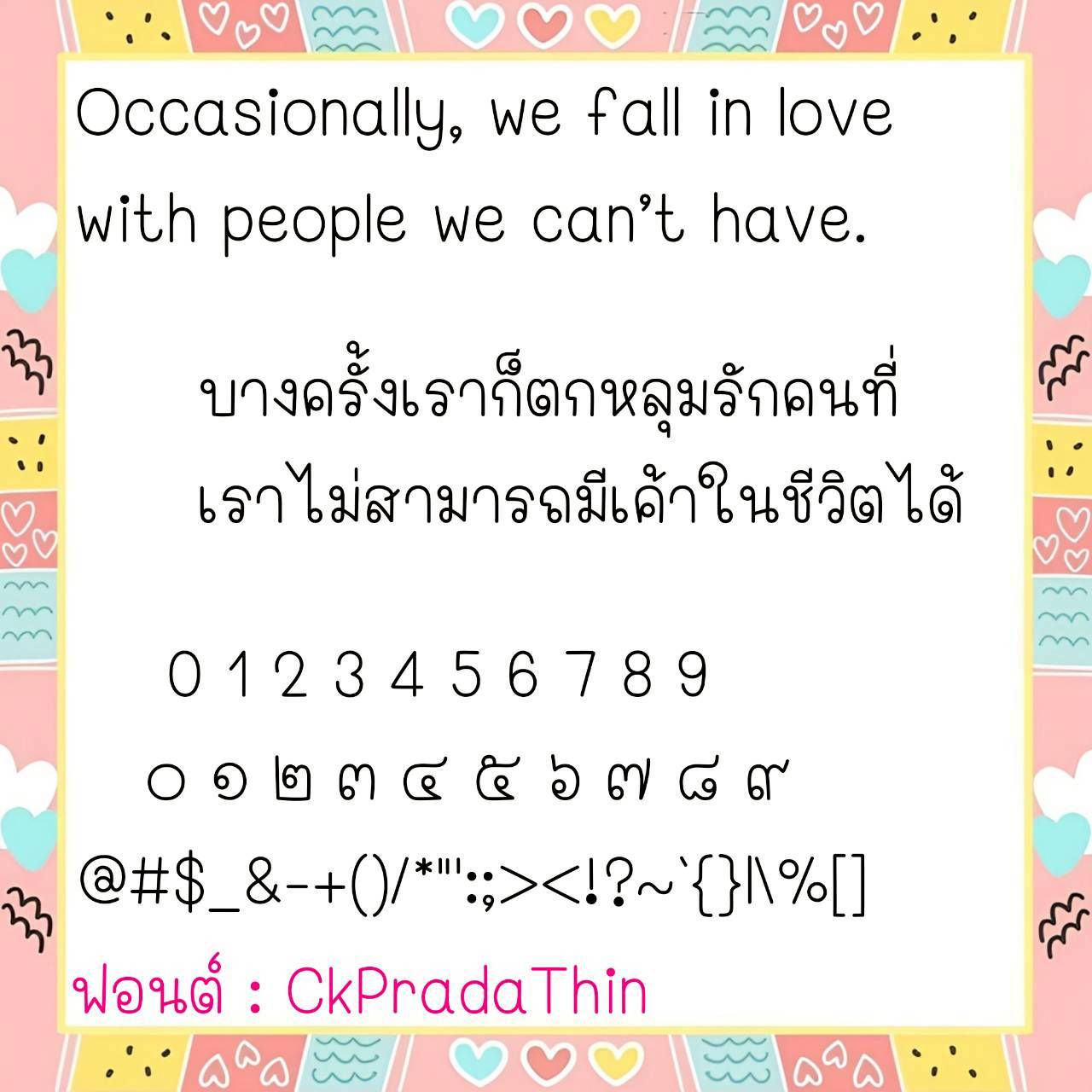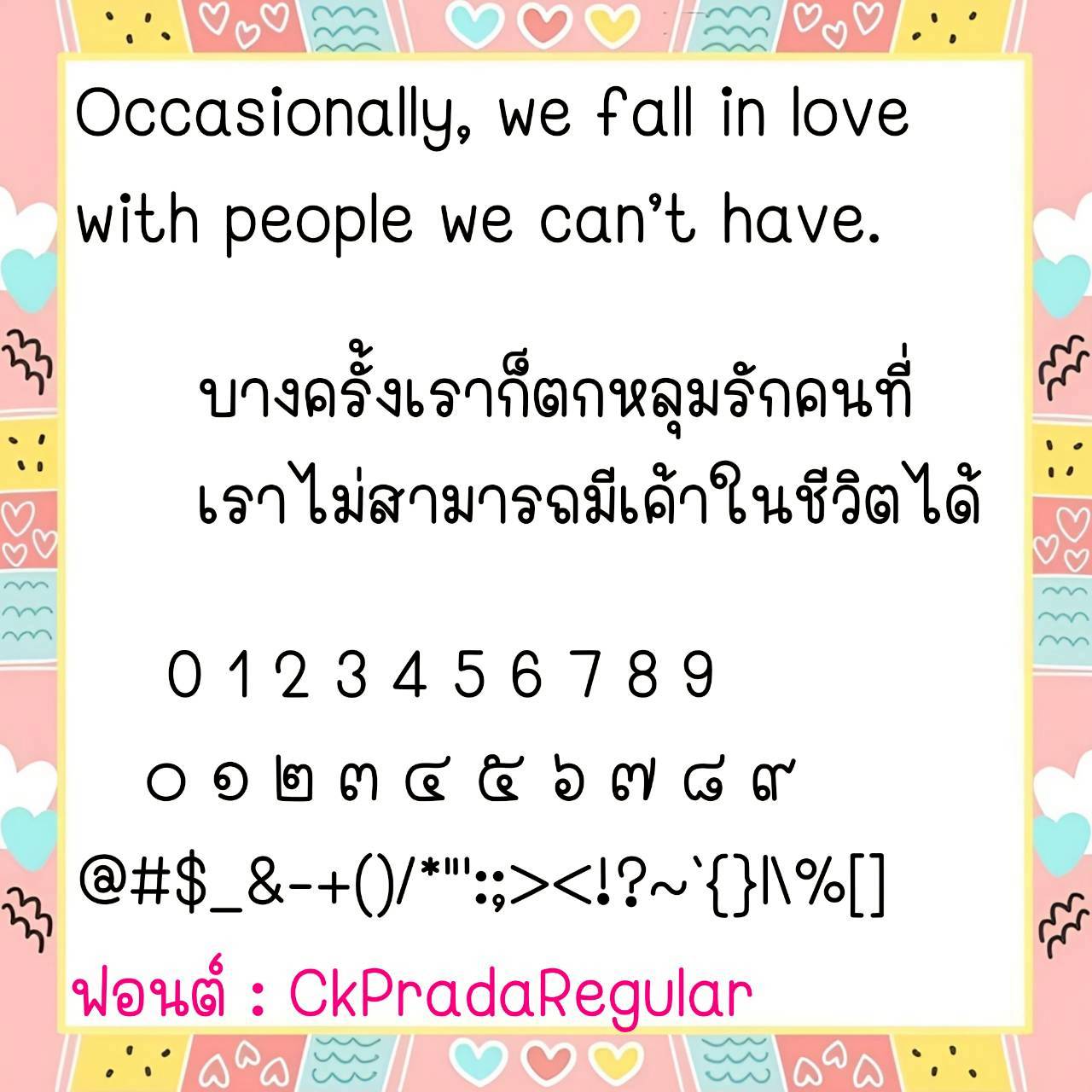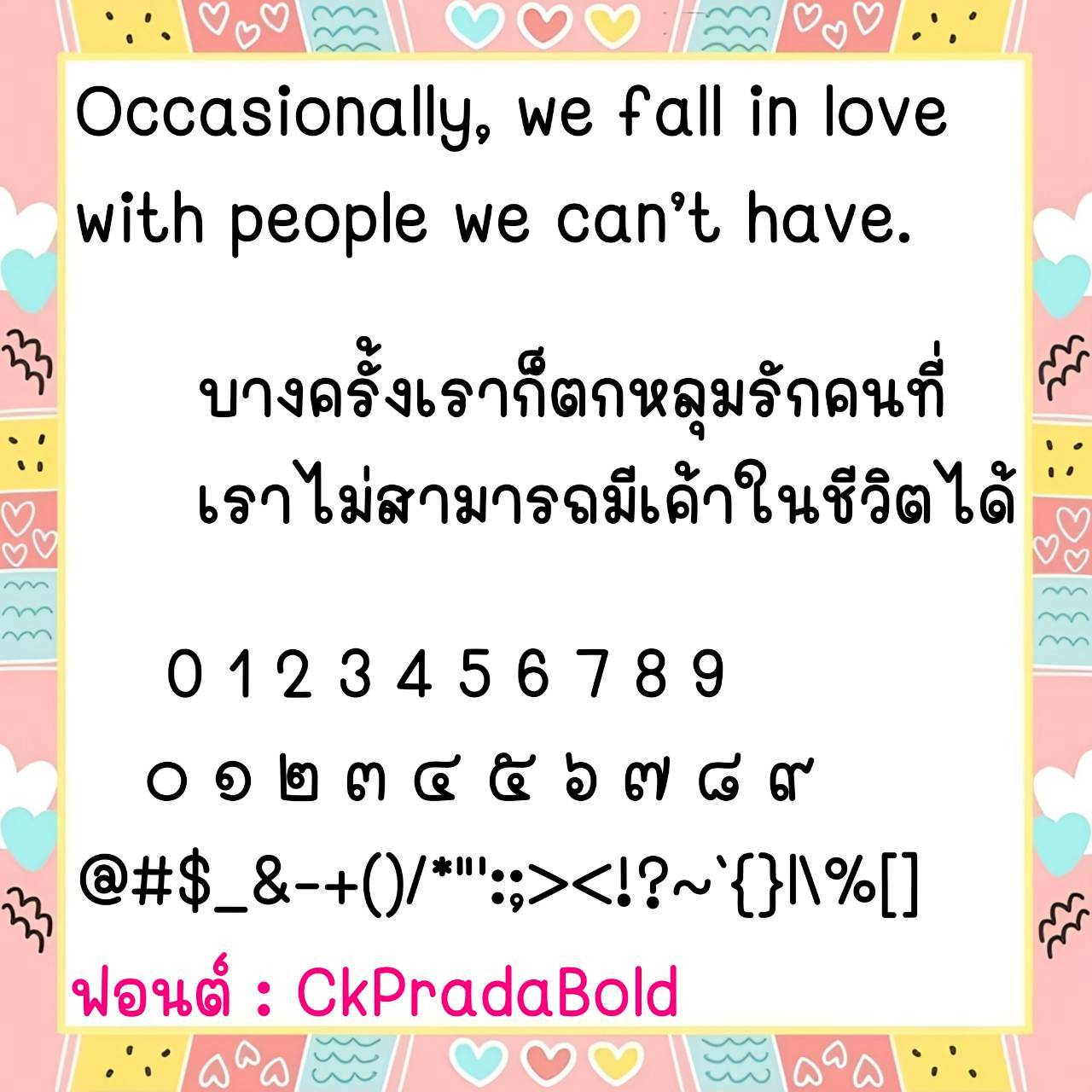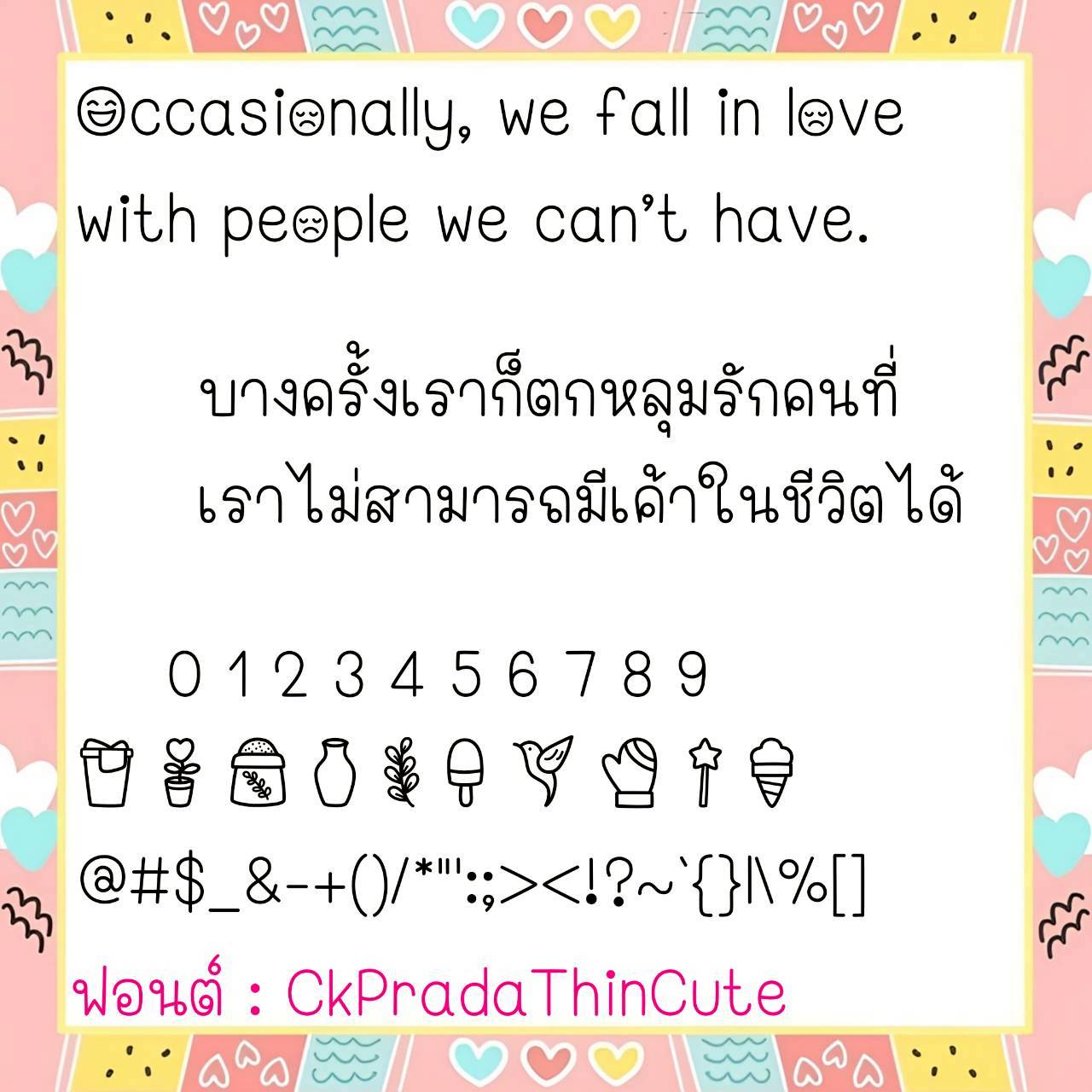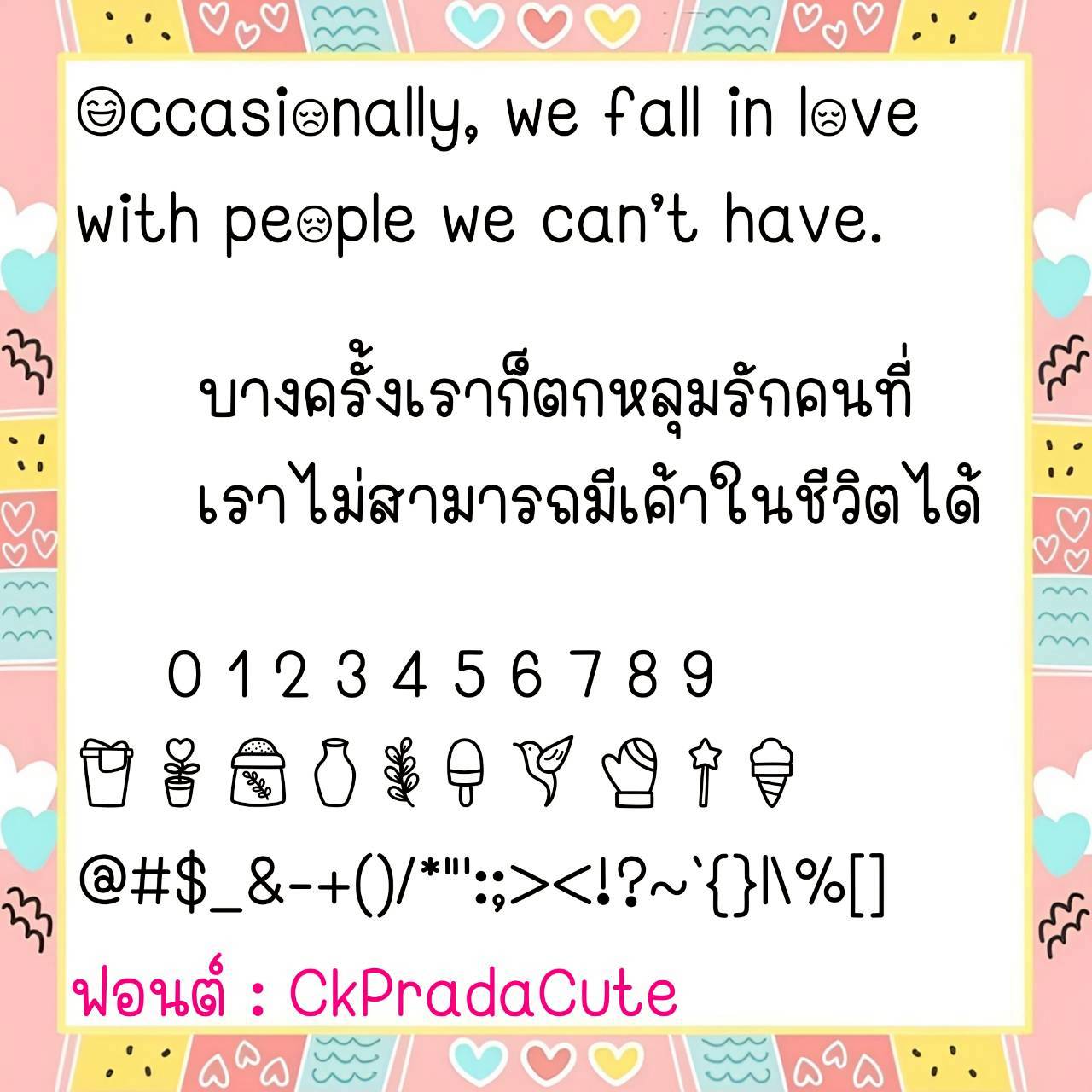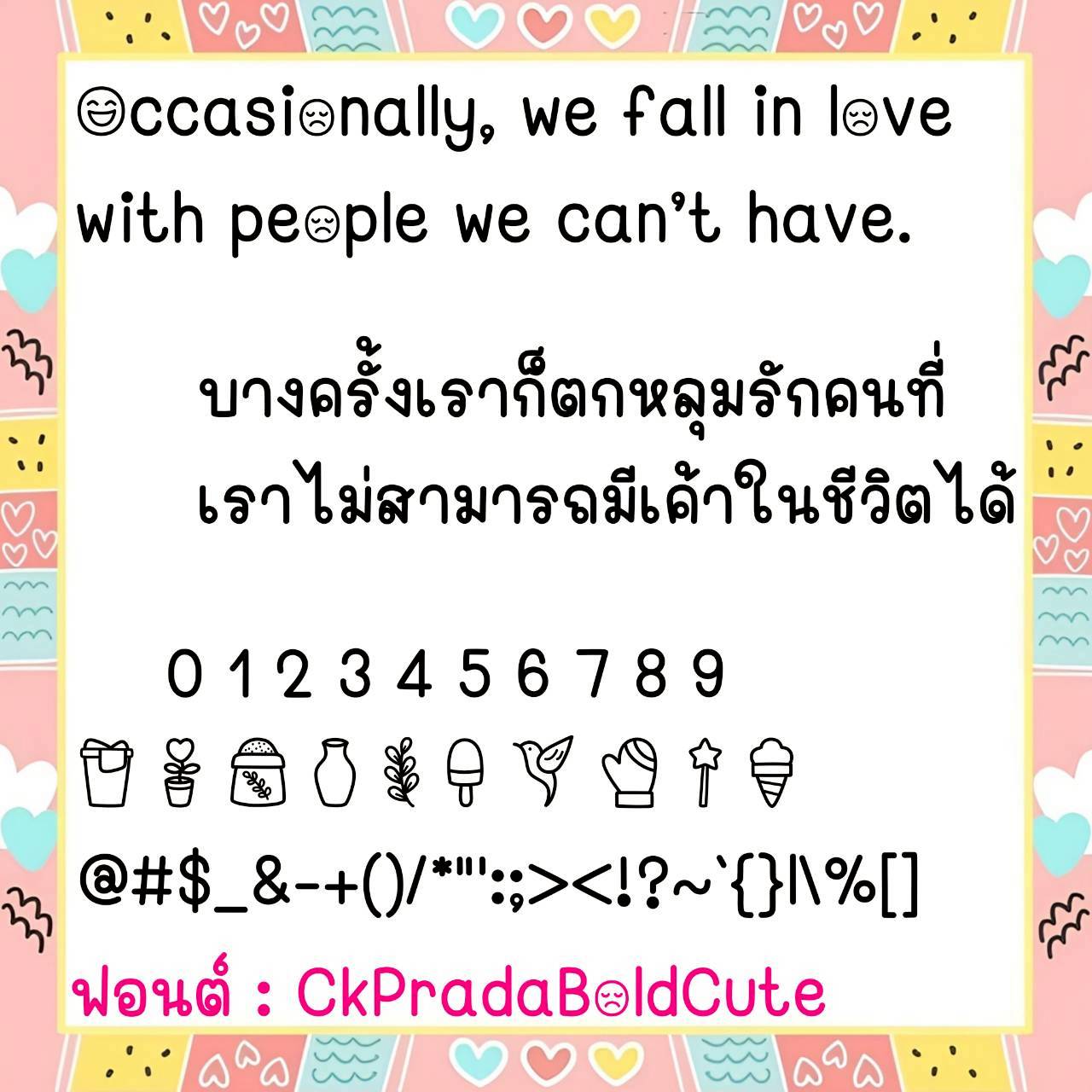
Font CkPrada
🔸 ฟอนต์ลายมือตัวแนวกึ่งเรียบร้อย ขนาดตัวกำลังพอดี ดูมีความเป็นระเบียบ อ่านง่ายสบายตา และยังมีไฟล์อิโมจิน่ารักๆ ที่ใช้แทนเลขไทยให้ด้วยค่ะ 🥰💙
🔹 This semi-neat handwritten font is just the right size, looks neat and easy to read, and also includes cute emoji files that can be used to represent Thai numerals. 🥰💙